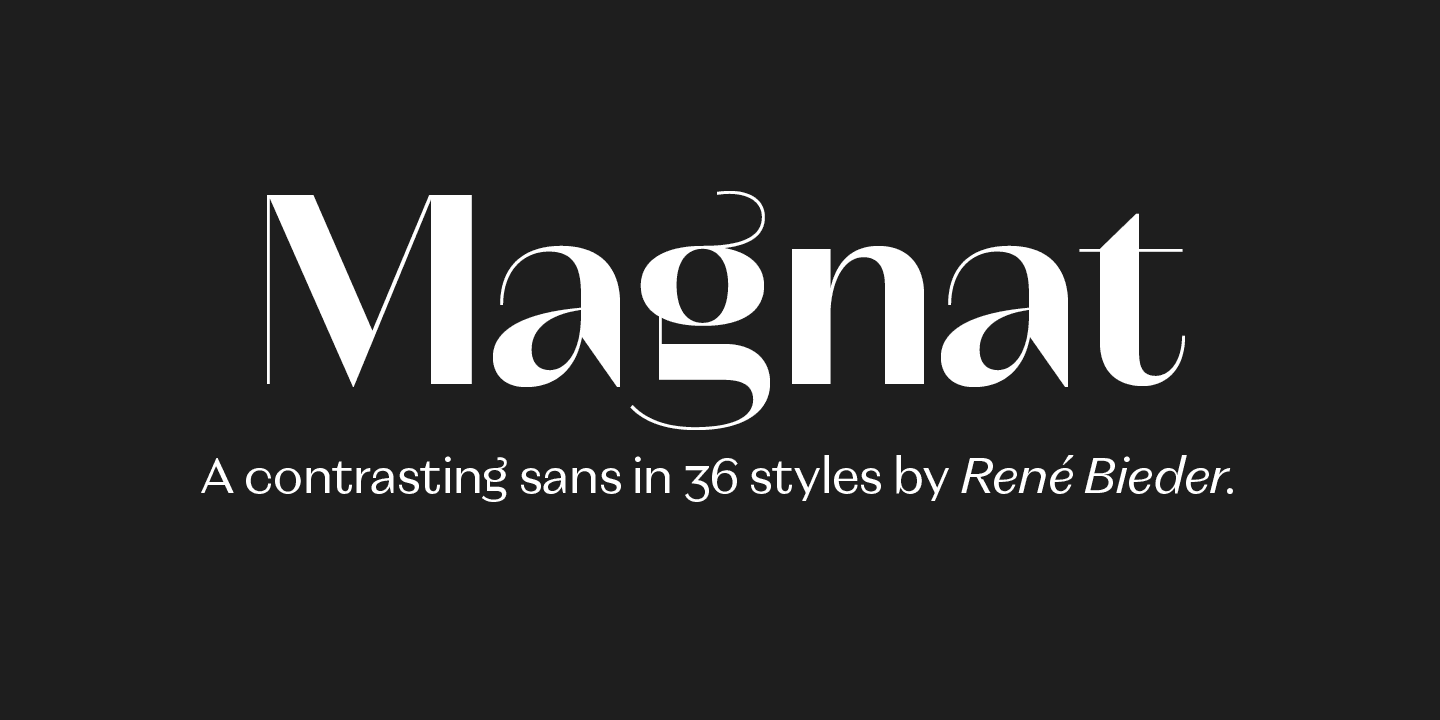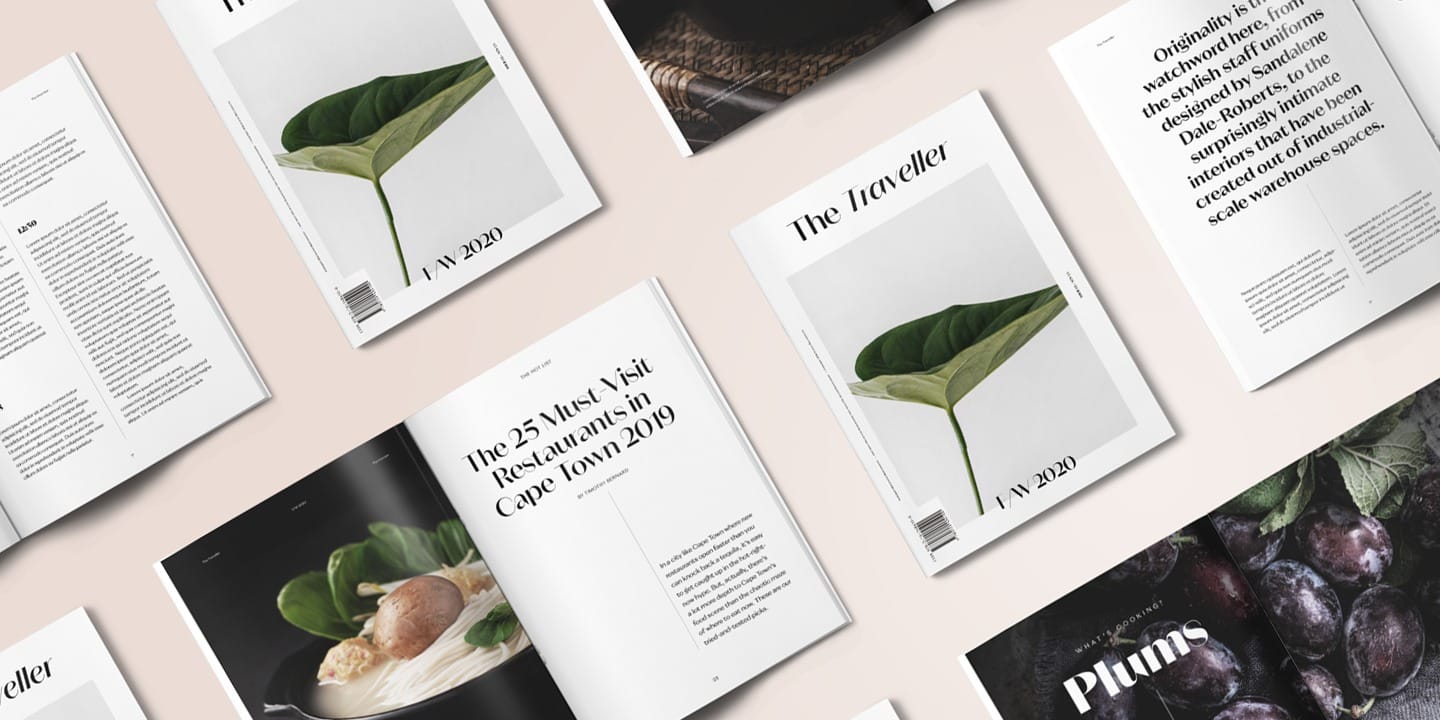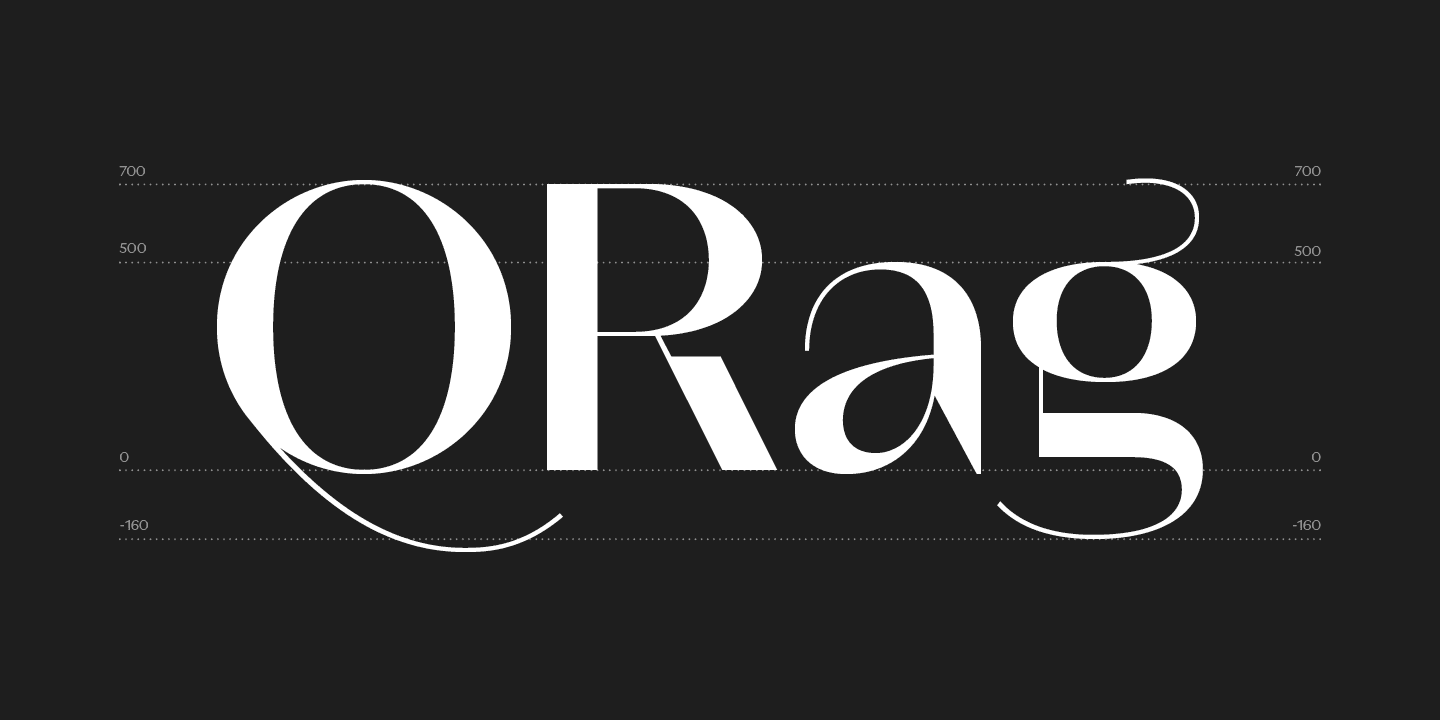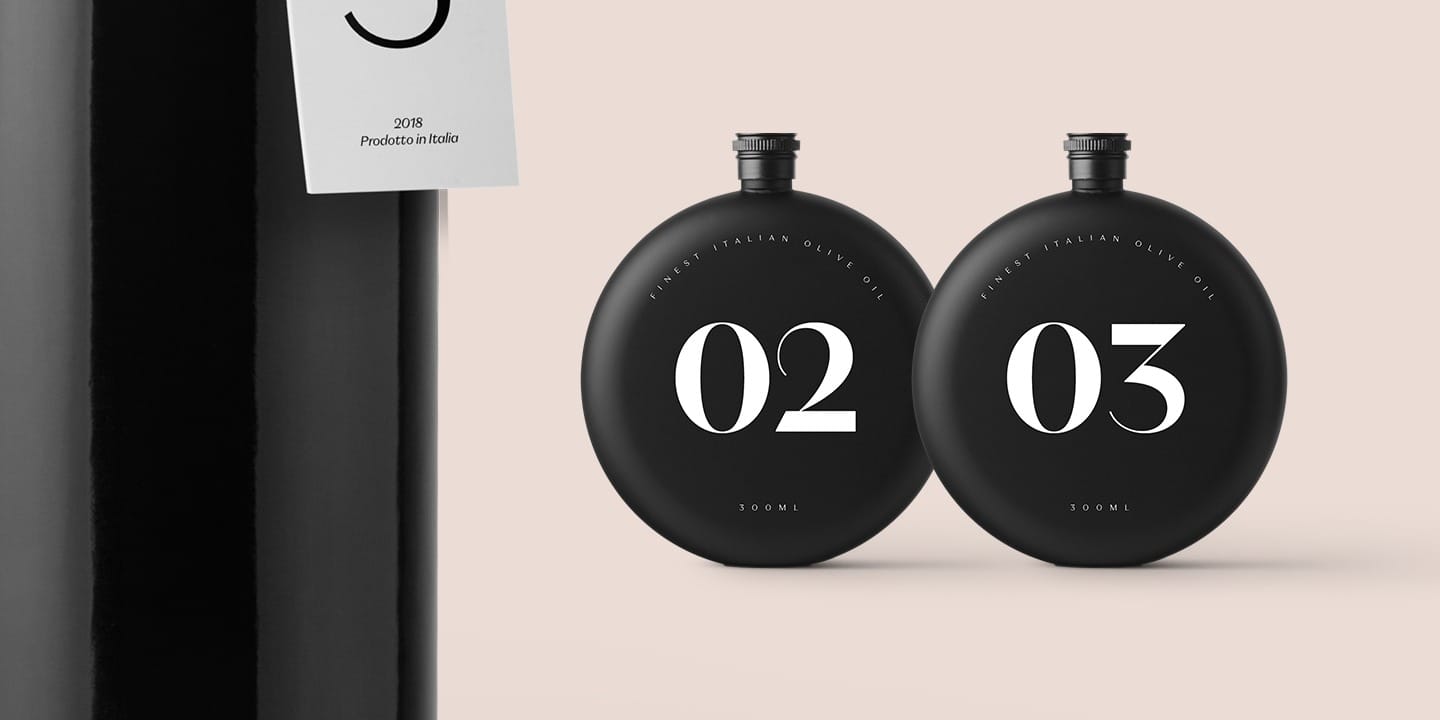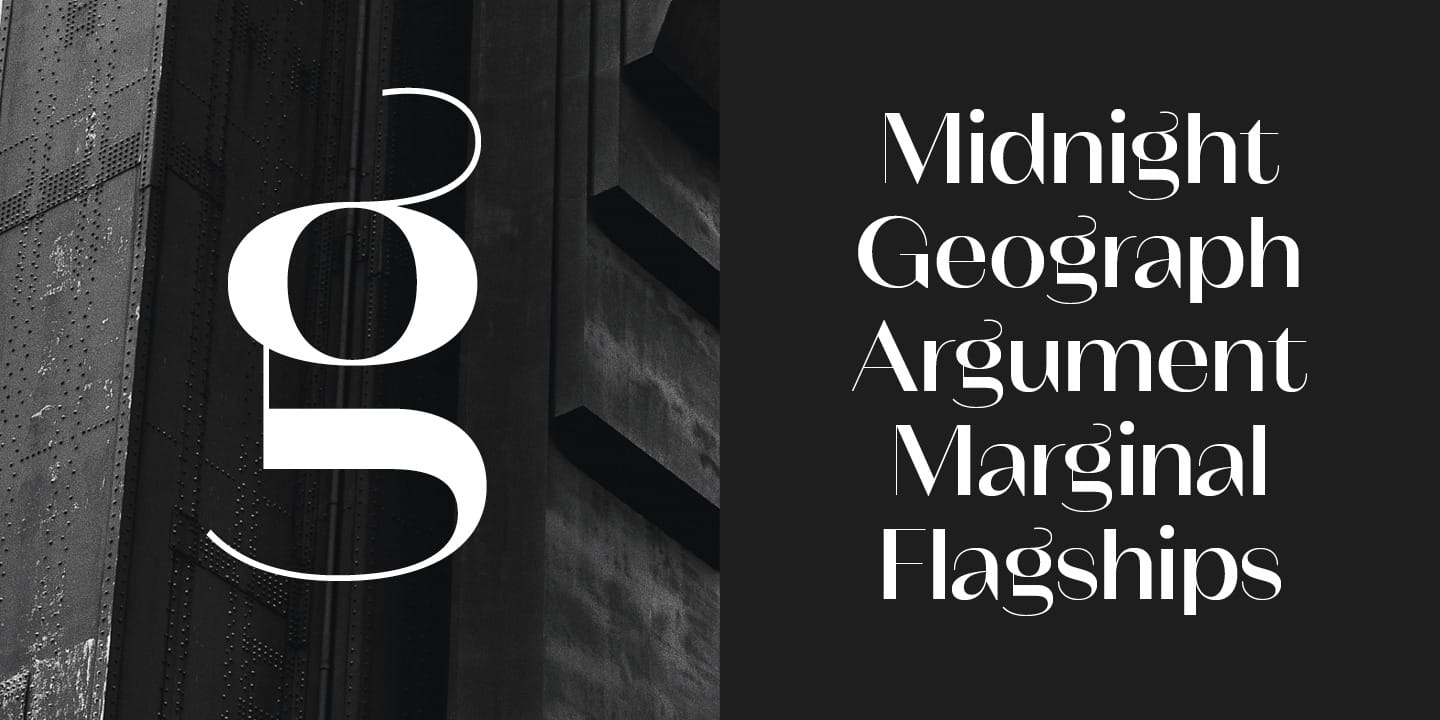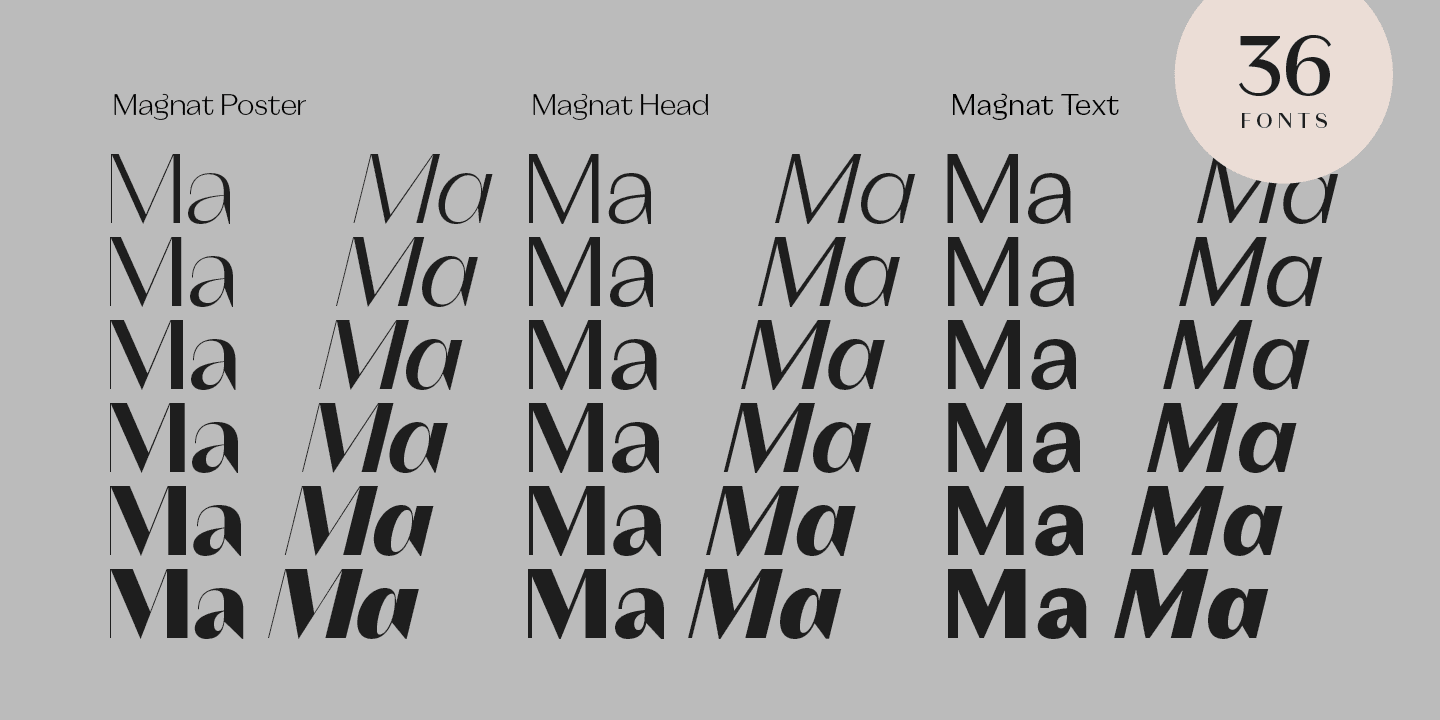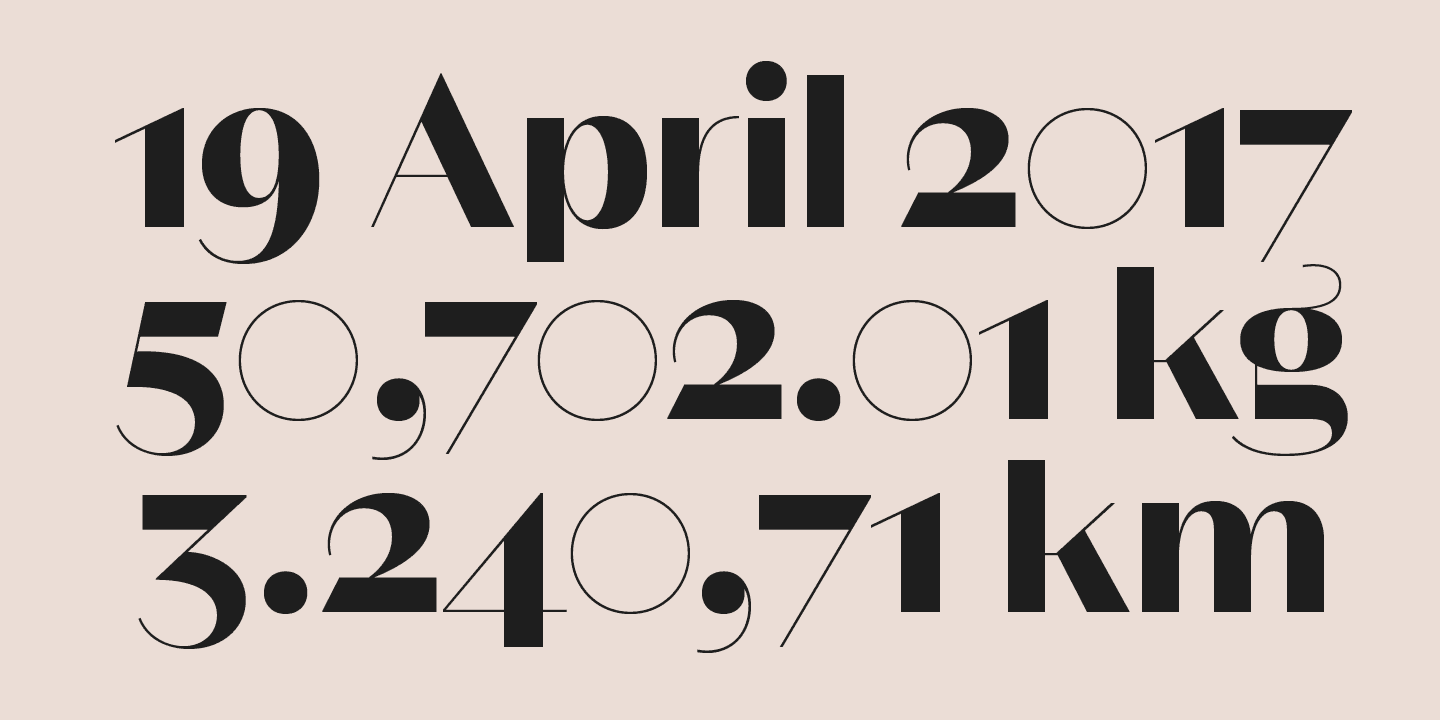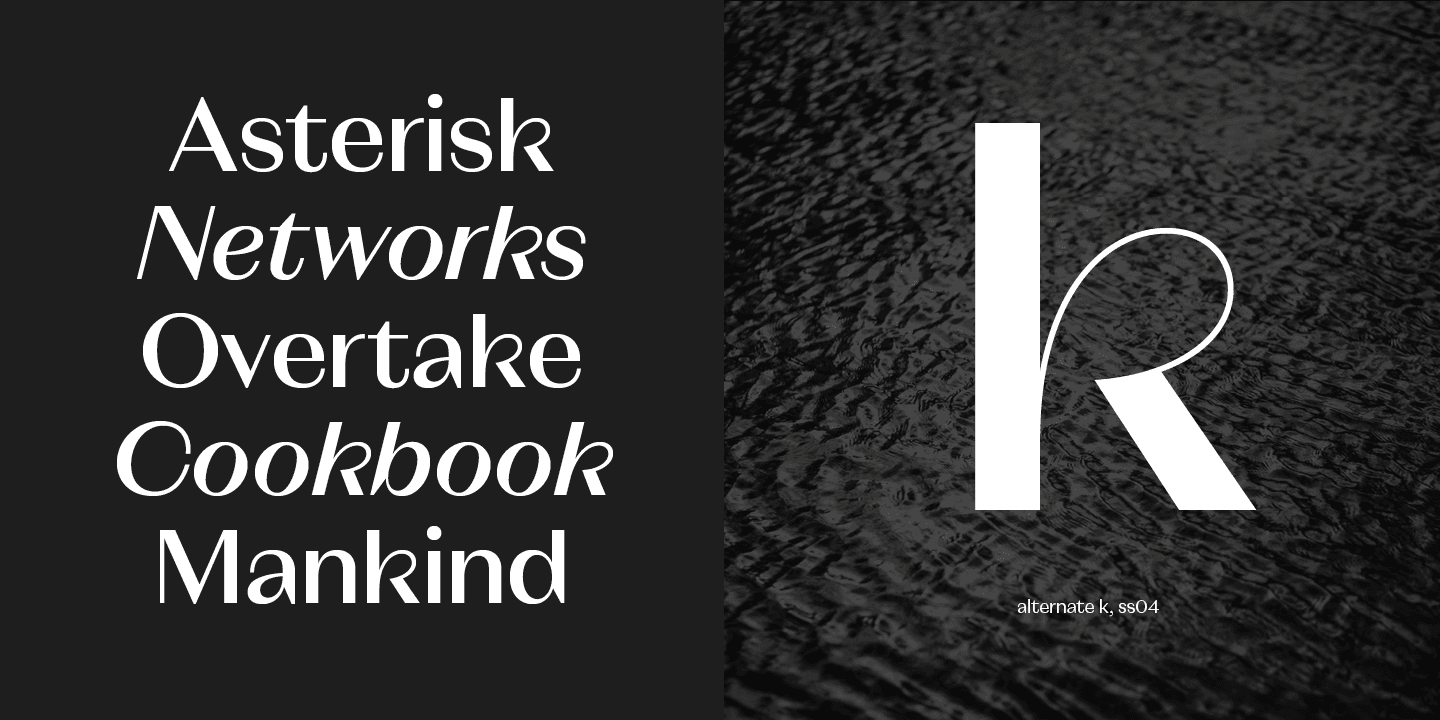
Magnat là một font lấy cảm hứng từ các thiết kế từ đầu thế kỷ 20 và mở rộng chúng thành một thiết kế đương đại. Các yếu tố đặc biệt như chữ g viết thường hoặc đuôi dài ở chữ Q viết hoa phá vỡ sự nghiêm khắc và thêm tính cách thú vị và khác biệt.
Magnat Font Family có sẵn với 36 kiểu font bao gồm cả chữ in nghiêng phù hợp, được chia thành 3: Poster, Head và Text. Mỗi loại đã được thiết kế cho phạm vi kích thước văn bản riêng của nó để dễ dàng tạo ra các thiết kế ấn tượng và phụ hợp.
Mỗi kiểu phông chữ được trang bị nhiều tính năng opentype như các ký tự thay thế, các bộ số khác nhau hoặc các hình dạng phân biệt chữ hoa chữ thường, làm cho nó trở thành lựa chọn hoàn hảo cho thiết lập kiểu chuyên nghiệp trong xây dựng thương hiệu, biên tập hoặc thiết kế kỹ thuật số.